Googleマップに見慣れないフォントが!
近所のスーパーの周辺をGoogleマップの航空写真で調べていたら、
隣の建物に見慣れないフォントが。
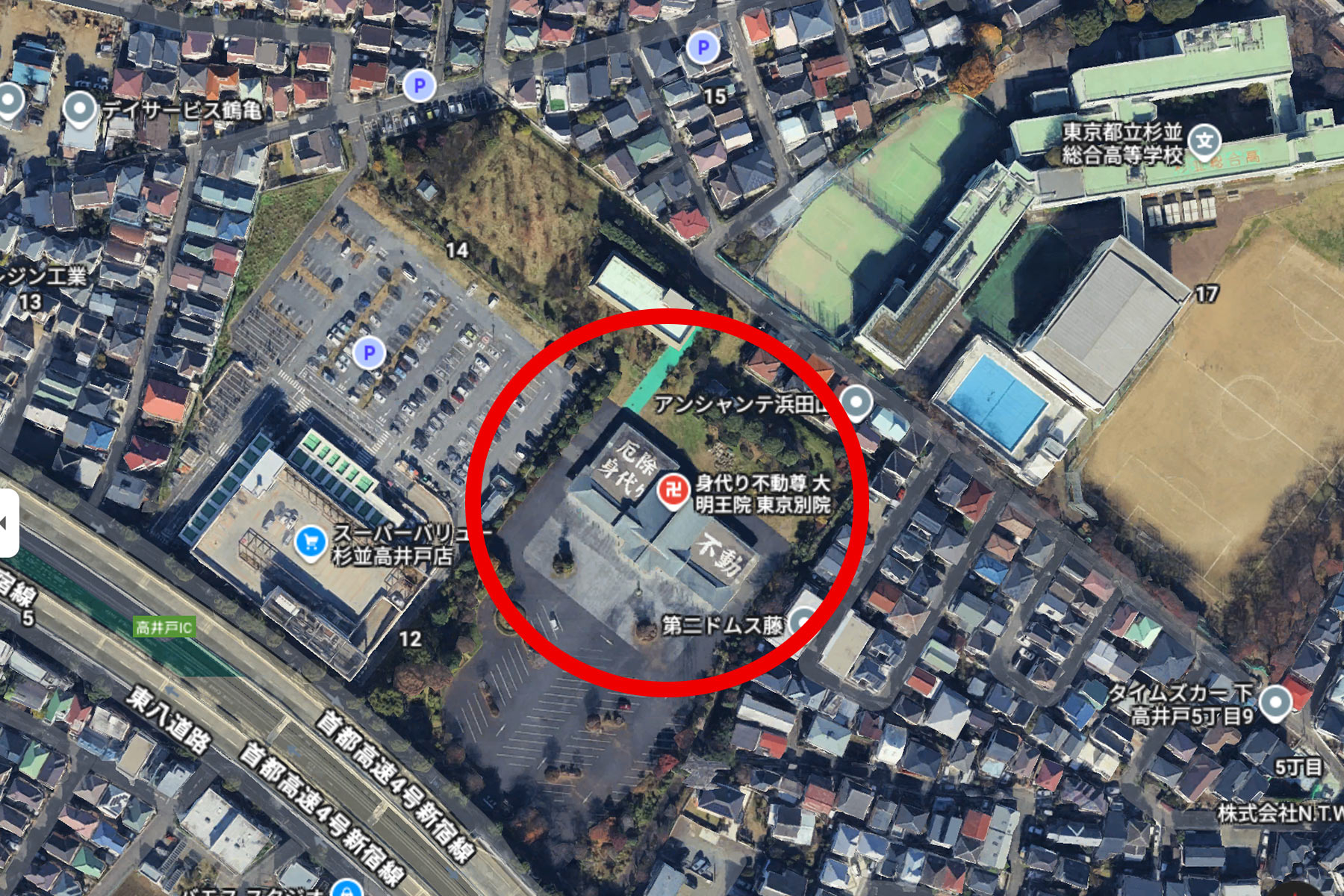
んー、Googleマップに明朝体で説明文?
なんか変だなーと思って拡大してみると、、
どうやら、お寺の屋根に大きく字が書いてあるようです。
誰向けの広告?ヘリコプター?
僕のように航空写真で見つけちゃった人向けでしょうか。
「厄」や「身代り」など、なんだか不吉な文字が出てきたので、
最初はちょっと怖かったです。
お寺のウェブサイトを見ると、他にも系列のお寺があるそうなので、
「もしや?」と思って調べてみました。
川崎本山にも、熱海別院にもなかったのですが、
あった!横浜別院には、おなじ文言がありました!
最近はこのようなMEO(Googleマップで検索上位表示させる手法、SEOの地図版)が流行ってるんですかね。
クライアントに提案してみようかな。